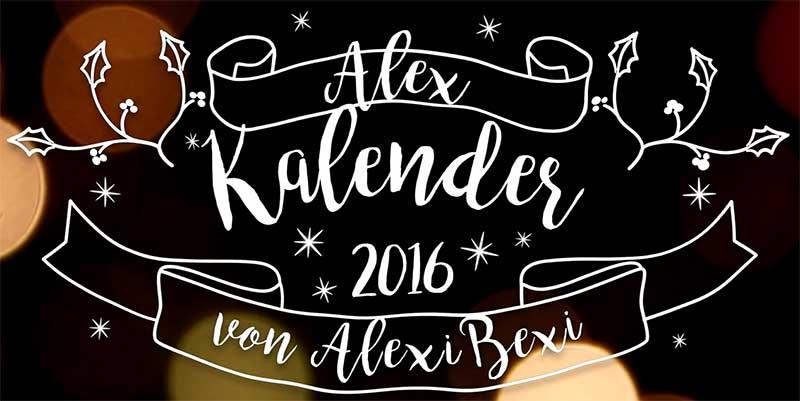
[Mitglied Desi…] Geschrieben Dezember 29, 2016 Teilen Geschrieben Dezember 29, 2016 Ich sehe ganz oft irgendwelche Schriftzüge mit derselben bzw. einer sehr ähnlichen Schriftart. Kennt einer von euch diese Schriftarten und wo kann ich diese finden? Ich bin hobbymäßiger Grafikdesigner und finde diese Schrift richtig cool, weiß aber leider nicht, wie sie heißt! Link zu diesem Kommentar
Beste Antwort [Mitglied c8de…] Geschrieben Dezember 29, 2016 Beste Antwort Teilen Geschrieben Dezember 29, 2016 bromello. http://www.ffonts.net/bromello.font?text=Kalendr Link zu diesem Kommentar
[Mitglied Call…] Geschrieben Dezember 30, 2016 Teilen Geschrieben Dezember 30, 2016 Wäre es für Dich als Grafikdesigner nicht auch eine Option, zum Pinselstift zu greifen und so etwas selbst zu schreiben? Mit etwas Übung bekommst Du das schon hin. Link zu diesem Kommentar
[Mitglied 3fbf…] Geschrieben Dezember 30, 2016 Teilen Geschrieben Dezember 30, 2016 Das ist auch nicht so einfach, schnell mal ein einigermaßen gleichmäßiges Schriftbild hinzukriegen – gerade wenn man's hobbymäßig™ macht Wenn man's kann wird es aber deutlich dynamischer als mit einem Font … Mittlerweile gibt es aber so viele Schriften in der Richtung, teilweise auch mit Alternativzeichen. Guck doch mal bei mightydeals nach Script fonts http://www.mightydeals.com/deal/20-fabulous-handwritten-fonts.html http://www.mightydeals.com/all_deals?s=Script+fonts Link zu diesem Kommentar